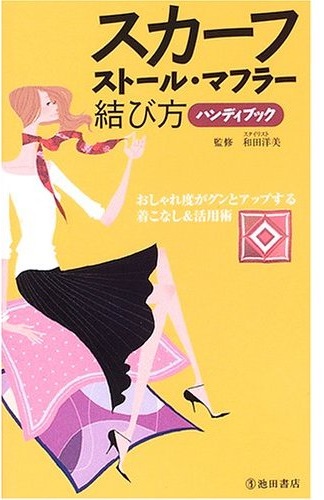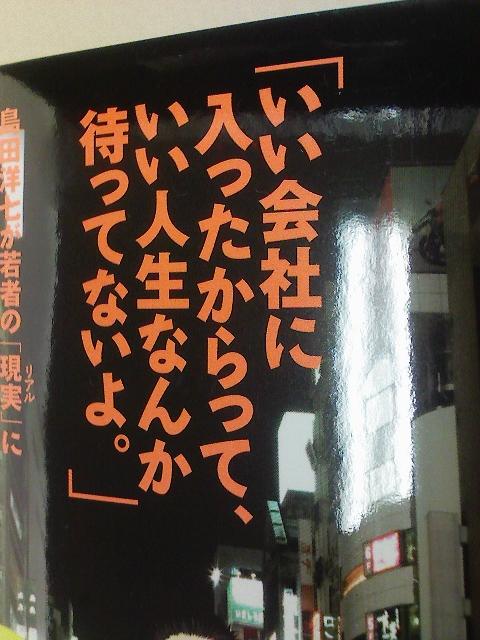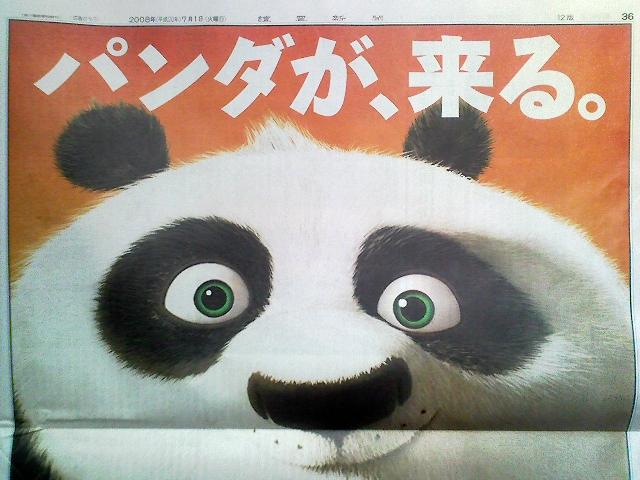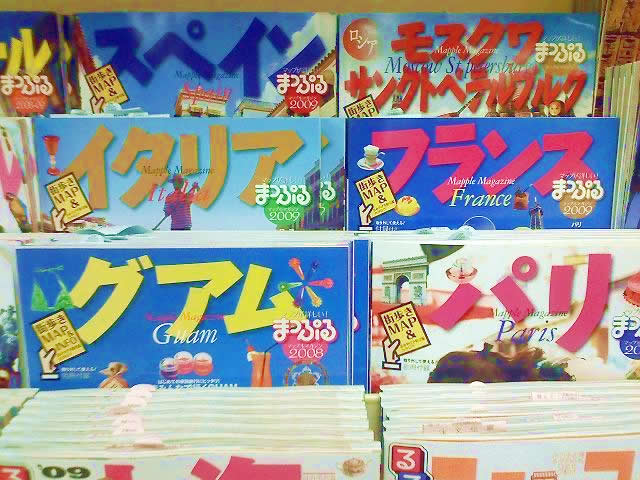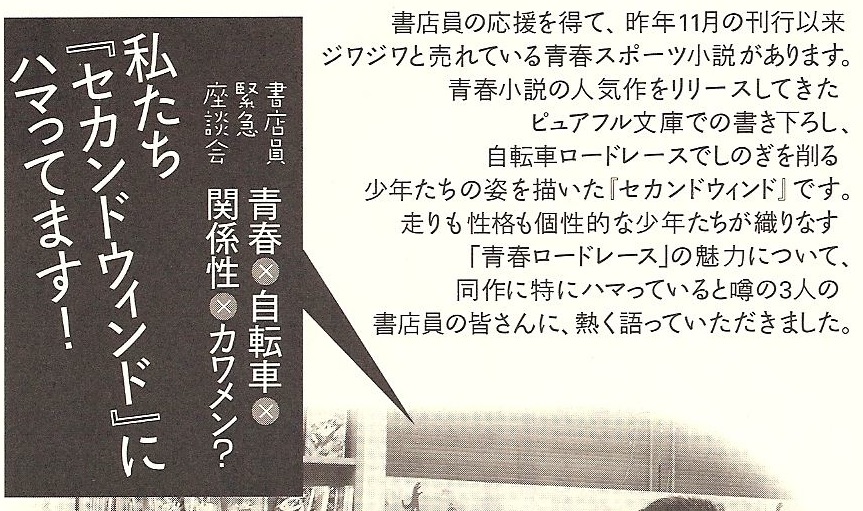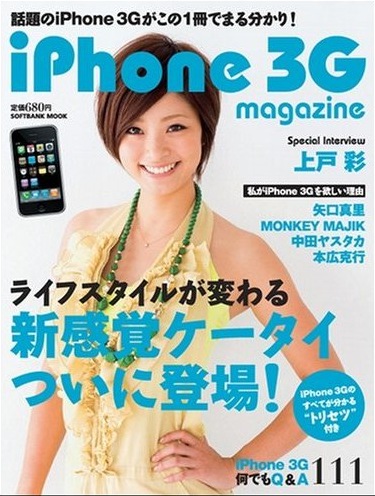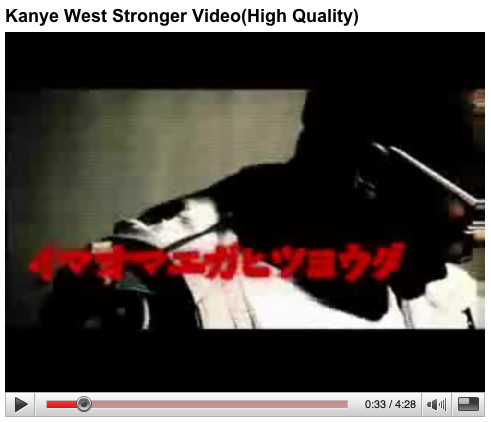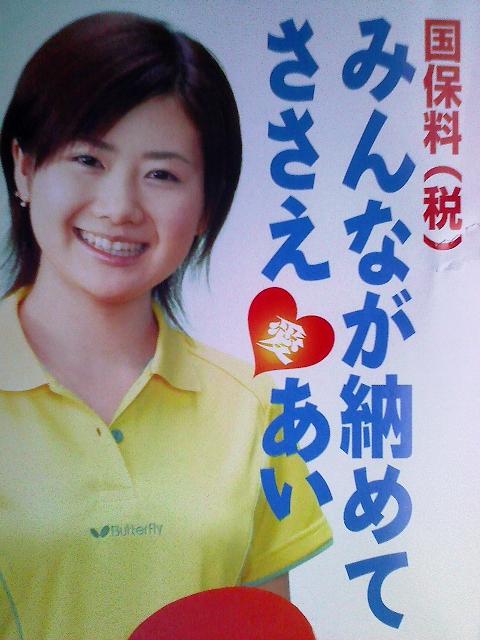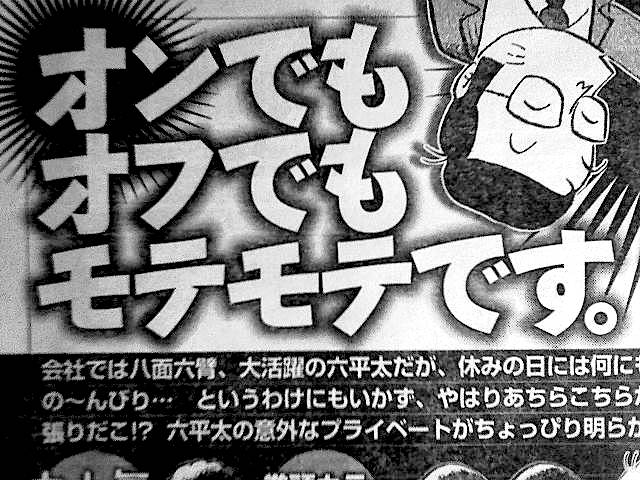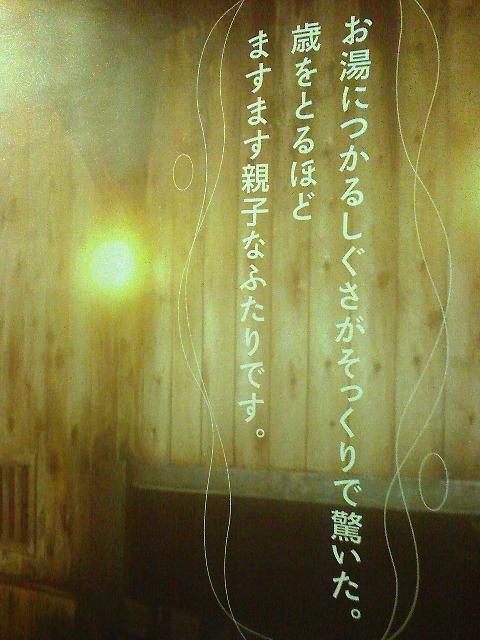
料理本  さとうゆたか  2011年7月20日(水) 17:02
書名:つくりおき基本レシピ
著者:河野雅子
発行:高橋書店
表紙  さとうゆたか  2011年6月4日(土) 14:28
書名:テッドがおばあちゃんを見つけた夜
著者:ペグ・ケレット
翻訳:吉上恭太
発行:徳間書店
ディズニードリルシリーズ  さとうゆたか  2011年5月28日(土) 9:46
画像をクリックして拡大すると「えれがんと」も使われているのが判ります…。
書名:入学準備〜小学1年のことばと文しょう
発行:学研パブリッシング
さとうゆたか  2011年5月28日(土) 9:47 [修正]
書名:入学準備〜小学1年のたしざん
発行:学研パブリッシング
さとうゆたか  2011年5月28日(土) 9:49 [修正]
書名:入学準備〜小学1年のかず・かたち・ながさ
発行:学研パブリッシング
さとうゆたか  2011年5月28日(土) 9:50 [修正]
書名:入学準備〜小学1年のひらがな・カタカナ
発行:学研パブリッシング
雑誌記事のタイトル  さとうゆたか  2011年5月18日(水) 15:41
芸能雑誌…だったかな。
ヘンな虫たち  さとうゆたか  2011年5月12日(木) 9:34
墨東ルイカが完成したので、
こちらで使われているのは、旧墨東フォントということになります…。
書名:ニッポンのヘンな虫たち
監修:日本昆虫協会
編集:アイランズ
発行:学研パブリッシング
DVD教本  さとうゆたか  2011年5月4日(水) 18:38
書名:やさしいヨガ教室—DVDで自宅レッスン!
監修:房前 光芳
発行:西東社
「あられ」「セプテンバー」も過去に購入させていただき、
お気に入りのフォントですが、またお気に入りフォントが
増えました。
総合書体「墨東ルイカ」  さとうゆたか  2011年4月25日(月) 20:38
漢字も含んだ総合書体です。よろしくお願いいたします。
早速購入させていただきました。端正なアニト(私の定番(#^.^#))も可愛いルイカも大好きですが、ゴシックなのに柔らかくて上品な墨東かなの魅力がたまらないです。ありがとうございました!
風味豊かな食パン  さとうゆたか  2011年4月23日(土) 20:41
知人が送ってきてくれた画像。
しっとりソフトな小麦粉本来の風味豊かな食パン…だそうです。
新聞広告  さとうゆたか  2011年3月15日(火) 16:30
今朝の新聞より。